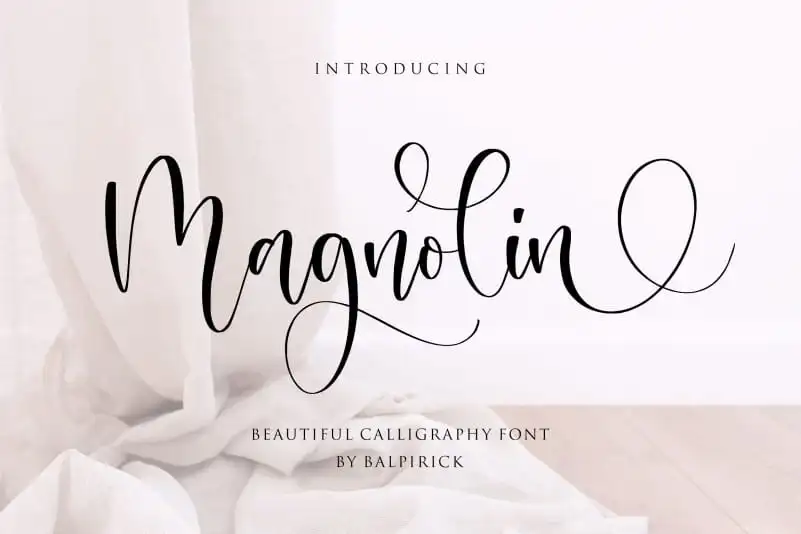
Magnolin Beautiful Calligraphy Font – Download Grátis
A fonte ‘Magnolin Beautiful Calligraphy Font’ é perfeita para diversos projetos que valorizam uma apresentação elegante e sofisticada. Seja você designer de embalagens, criador de marca ou editor de revistas, essa fonte trará um toque artesanal aos seus trabalhos. Suas linhas delicadas e harmoniosas são ideal para expressar mensagens em alto destaque sobre uma superfície mais elaborada, como na decoração de casamentos ou apenas para estilos personalizados que se destacam no background. Com sua utilização suave nas redes sociais ou em postagens de aniversário, você pode criar um visual encantador que chama a atenção do público. Ideal tanto para trabalhos comerciais quanto para expressões pessoais, a ‘Magnolin Beautiful Calligraphy Font’ oferece uma maneira única e sofisticada de destacar os elementos mais importantes no seu design gráfico.